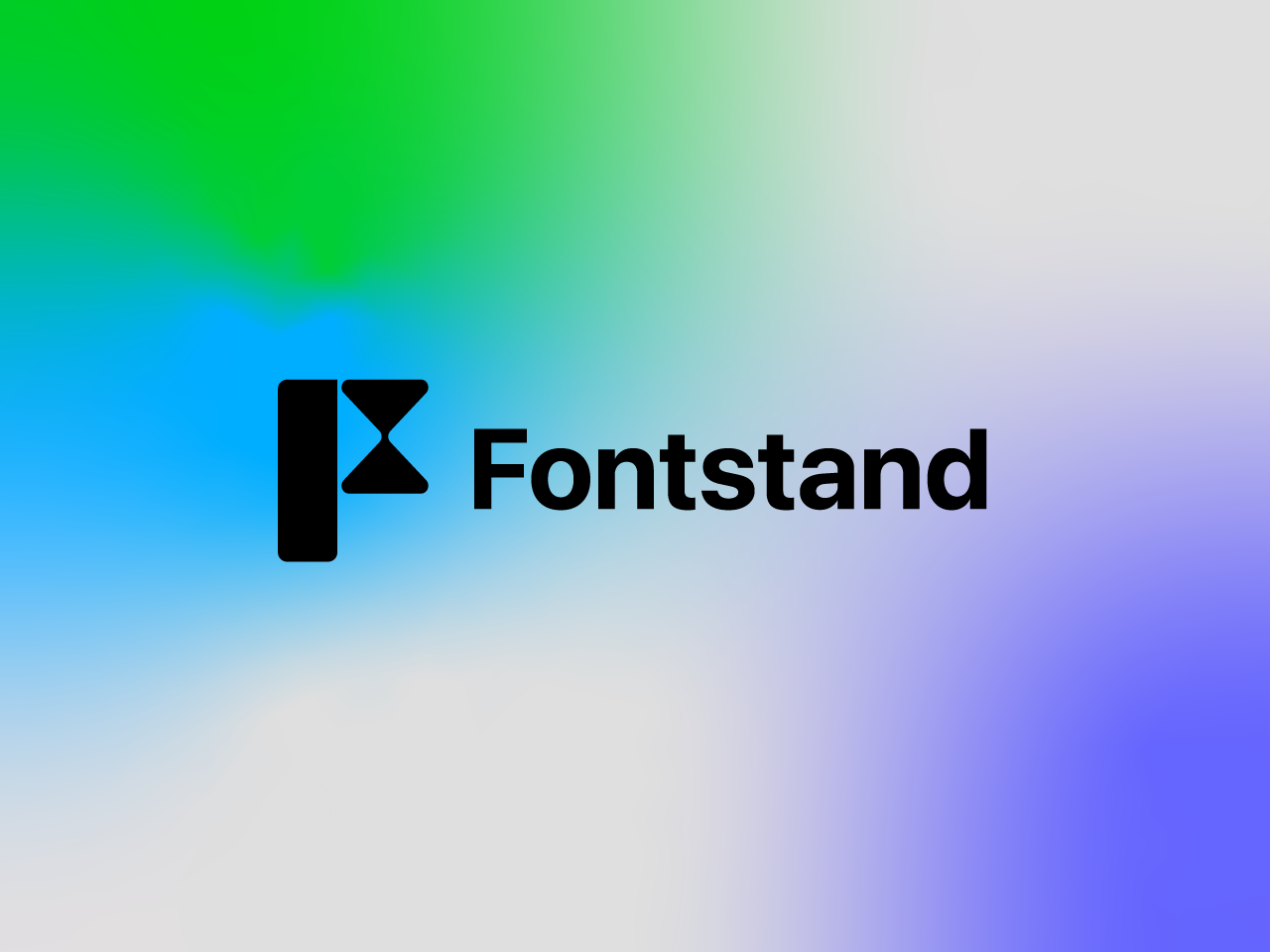
Fontstand
Fontstand je aplikácia pre Mac OS X a Windows, ktorá umožňuje testovanie písma zadarmo alebo jeho mesačný prenájom na použitie na počítači a webe za zlomok bežnej ceny.
Logo, použité aj pre ikonu aplikácie, kombinuje písmeno F s presýpacími hodinami, ktoré slúžia ako metafora pre základnú funkciu aplikácie – dočasné prenájmy písma. Zelená, modrá a fialová farba reprezentujú rôzne režimy prenájmu písma dostupné v aplikácii.